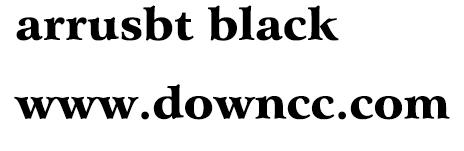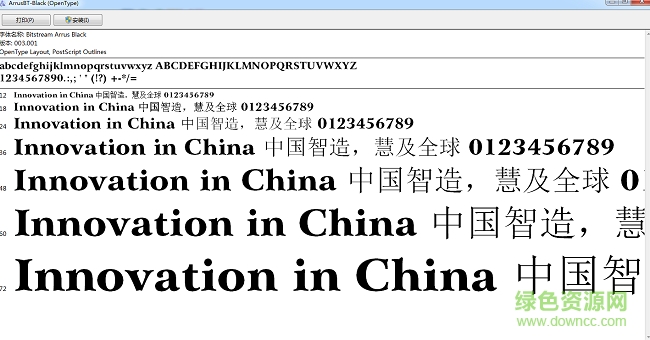
arrusbt blackitalic
arrusbt black字體是一款設(shè)計精美實用性強的英文黑體字體,綠色資源網(wǎng)為各位字體愛好者提供的字體包包含了arrusbt black和arrusbt black italic兩款字體,歡迎大家免費下載!
英文字體粗細表示
1.字體的粗細,英文用Weight一詞表示,越粗的字Weight就越“重”。
2.Weight的各種具體表 示方法從細到粗一般有:Light、Regular、Bold、 Extra Bold、Black等,
3.不過這些表示法并沒有統(tǒng)一的標(biāo)準(zhǔn),而且各Weight之間的比例關(guān)系亦因字體而異。
arrusbt blackitalic